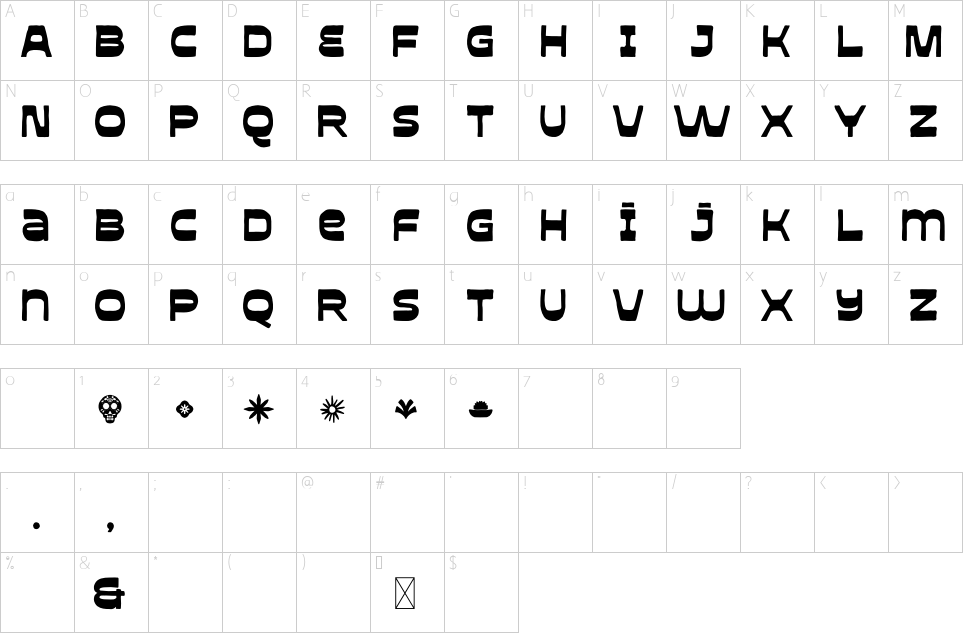
A Mezicola é uma fonte elegante e moderna, ideal para qualquer projeto gráfico que busque um equilíbrio entre sofisticação e simplicidade. Desenvolvida pela não informado, a Mezicola foi projetada para fornecer um estilo distintivo que combina facilmente com texturas digitais e elementos gráficos contemporâneos. Este estilo minimalista e bem equilibrado é perfeito para aplicativos de design gráfico, como o design de websites, gráficos de marketing e até mesmo para a criação de logotipos. Com seu design único e sua facilidade de uso, a Mezicola se destaca como uma opção versátil para qualquer designer que deseja adicionar uma pegada moderna ao seu trabalho. A fonte Mezicola foi baixada 274 vezes, demonstrando a sua relevância e popularidade no mercado de fontes gratuitas. Se você está procurando por uma fonte que pode tornar seu trabalho ainda mais impactante, a Mezicola pode ser a escolha perfeita.